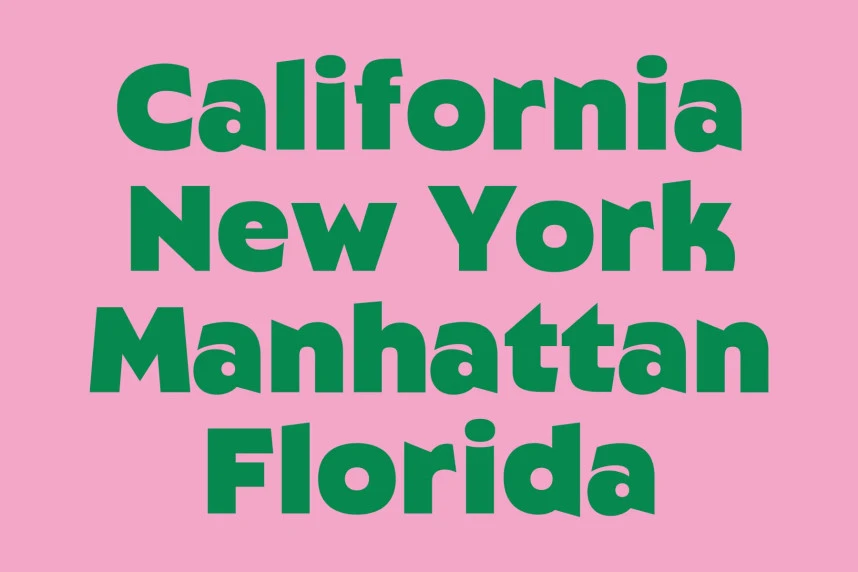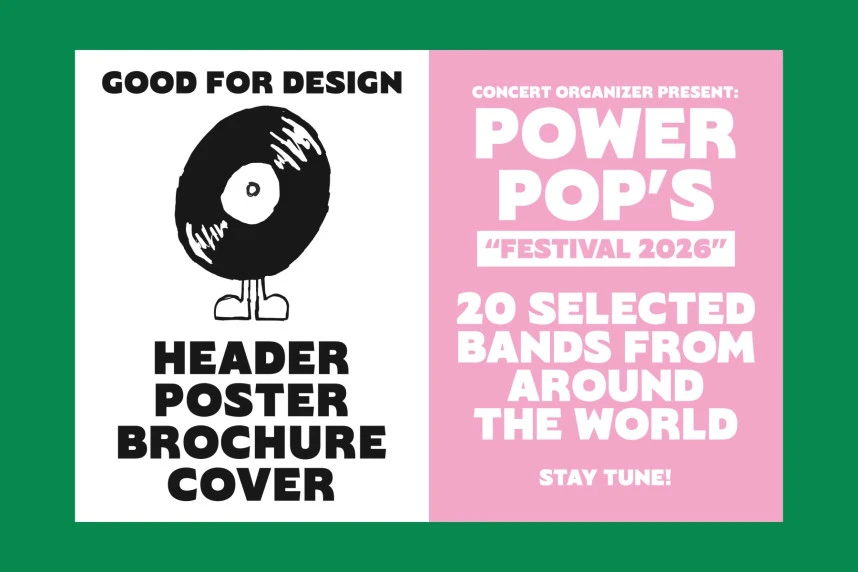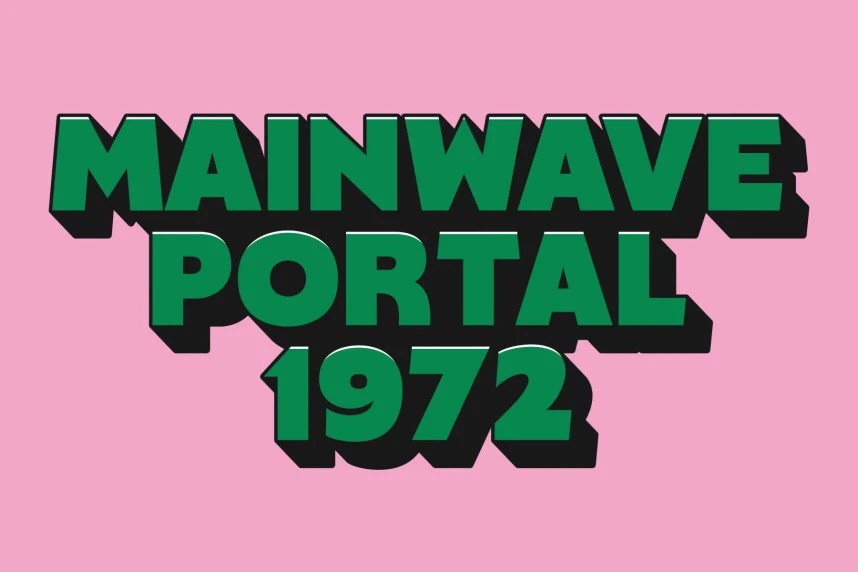
Konca HF Font
Konca HF Font, çarpıcı bir sans-serif gösterim yazı tipidir ve kalın Gotik yapıyı ham bir vintage karakterle sorunsuz biçimde birleştirir. İşlerinin dikkat çekmesini isteyen tasarımcılar için tasarlandı; bu yazı tipi logolar üzerinde maksimum görsel etki sağlar.
Konca HF Font, çarpıcı bir sans-serif gösterim yazı tipidir ve kalın Gotik yapıyı ham bir vintage karakteriyle kusursuz bir şekilde birleştirir. Çalışmalarının dikkat çekmesini isteyen tasarımcılar için tasarlandı. Bu yazı tipi logolar üzerinde maksimum görsel etki sağlar.